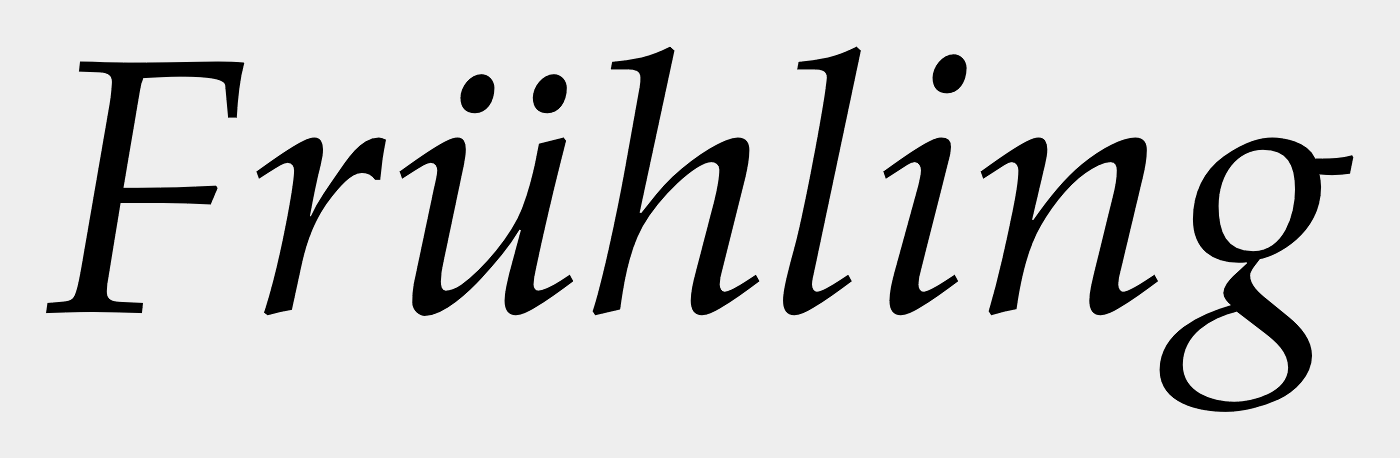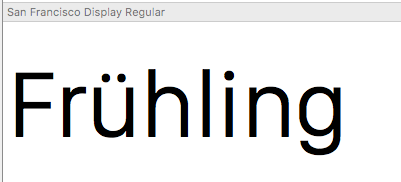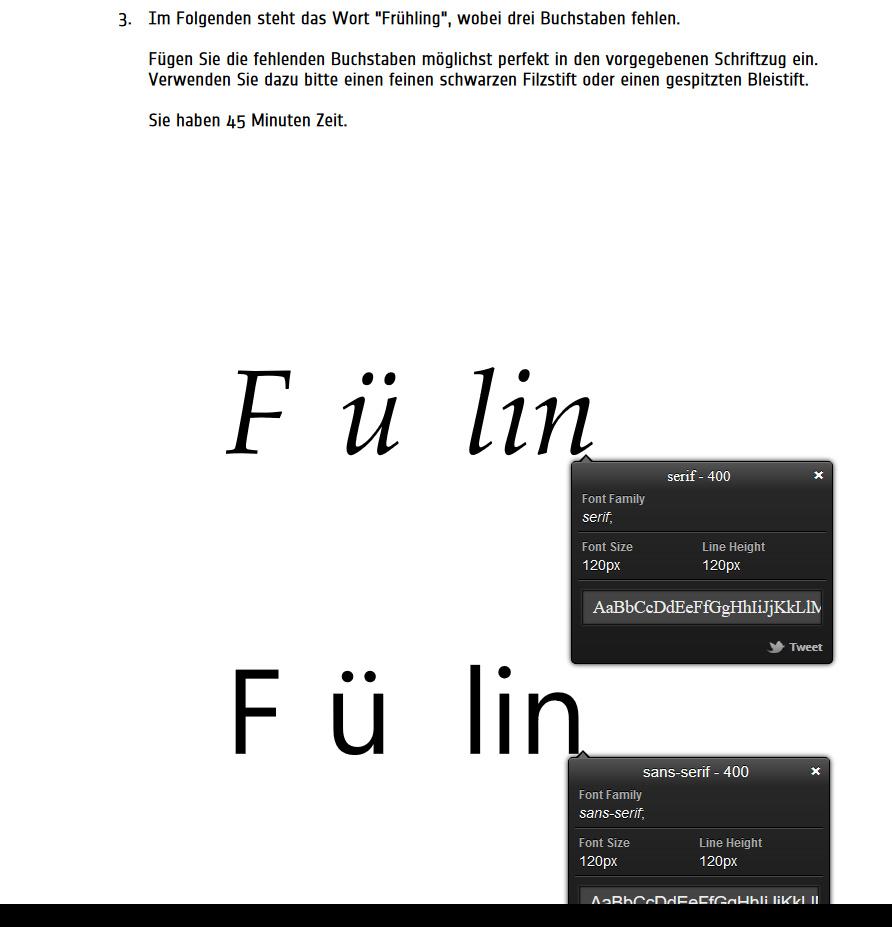
Schrift aus Übungsbeispiel
Ich habe hier zwei Übungsbeispiele, um Schriften zu vervollständigen.
Ich habe bereits whatsfont und fontfinder darauf angewendet aber die Ergebnisse scheinen mir unklar zu sein. (siehe Bild)
um nichts falsches einzuüben würde ich gerne mit Gewissheit wissen um welche Schriften es sich handelt um sie korrekt einstudieren zu können.
Die Sans kenne ich nicht, jedenfalls käme die "San Francisco" von Apple sehr nahe, mit den runden Punkten formal sowieso.
Hätte das r und das g bei der Palatino ganz falsch eingeschätzt.